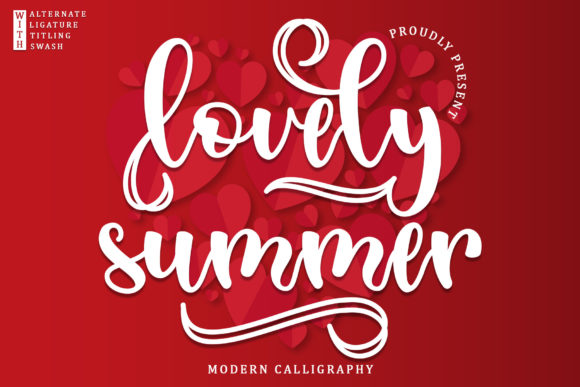
[Creativefabrica] Lovely Summer Font (2021)
Lovely Summer - романтичный и милый каллиграфический шрифт с символами, которые танцуют вдоль базовой линии.
Он добавит роскошную искру в любой дизайнерский проект, который вы хотите создать!